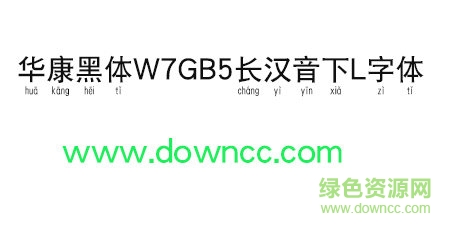
華康黑體W7GB5長(zhǎng)漢音下L字體是一款非常有特色的華康字體軟件,字體端正行云流水,非常適合于廣告設(shè)計(jì)、圖文印刷等多種領(lǐng)域,一鍵安裝便可好免費(fèi)使用,即能彰顯個(gè)性,又能讓你的設(shè)計(jì)面板更加美觀哦,需要的朋友可別錯(cuò)過了。
【黑體】
清末萌芽57年簡(jiǎn)化字體后定形。筆劃橫平豎直,粗細(xì)一致,筆劃較粗,方頭方尾形成方黑一體而得名,又稱方體。特點(diǎn):由宋體結(jié)構(gòu),筆劃單純,相互大方,醒目粗壯。